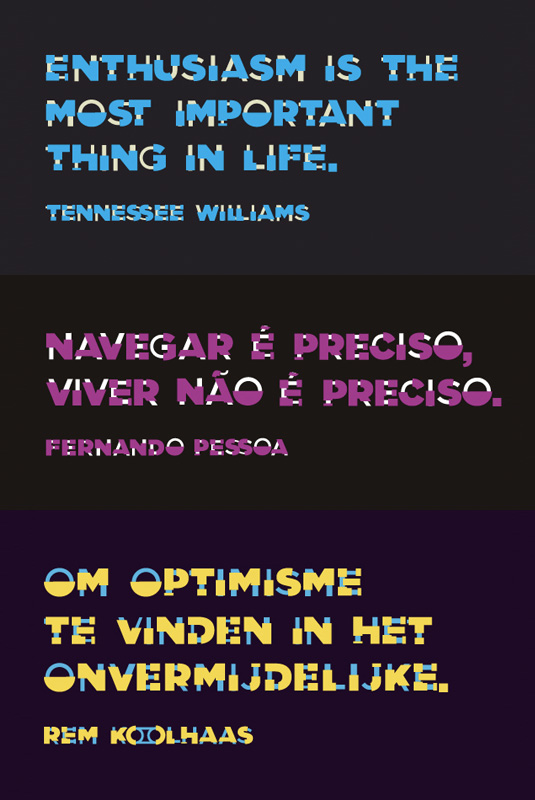
Font Design: Morning Glory
Il Font Design di oggi è: Morning Glory (download)
La realizzazione di questo font è opera del pittore, grafico e designer tipografico Armesilla Luis.
La particolarità di questo carattere è l’incastro di due o più elementi allo scopo di formare ogni lettera. Sicuramente idoneo per titoli sgarcianti, ma non certo per testi o sottotitoli.
Ecco alcuni esempi:
Possono essere usate una grandissima varietà di combinazioni di colori per un design accattivante come mostra il seguente video di presentazione al font Morning Glory in full HD: